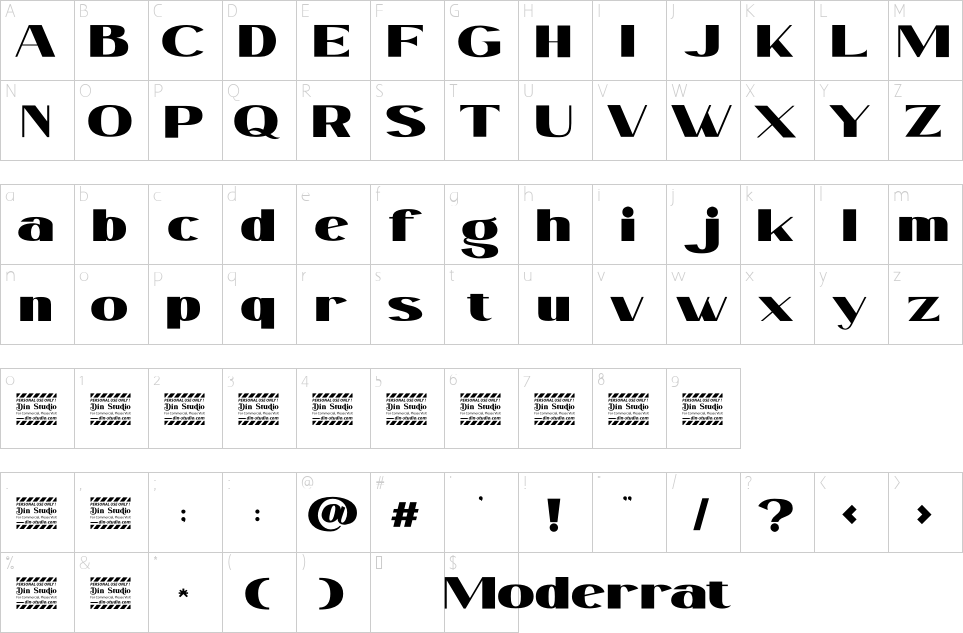
Moderrat é uma fonte livre e gratuita que oferece um toque único e moderno para seus projetos digitais. Esta font foi criada pela Din Studio e já foi baixada por 2,472 usuários. Moderrat combina facilmente entre o moderno e o vintage, proporcionando um estilo distintivo a qualquer projeto. Com um design cuidadosamente detalhado, essa font é perfeita para aplicativos de celular, design gráfico, e até mesmo para criação de logotipos. O download de Moderrat é uma ótima opção para designers que buscam recursos gratuitos de alta qualidade para seus projetos.